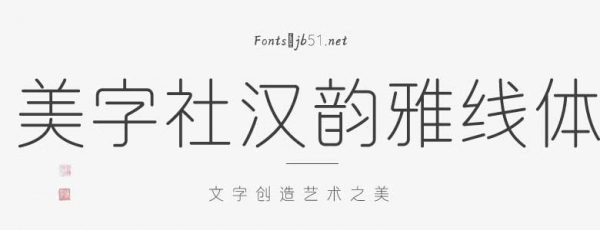
美字社汉韵雅线体晕染版
美字社汉韵雅线体晕染版以汉印和篆书结合,以极简设计手法创作的具有现代中国风的字体。字体融合了汉印的布局方正平直与篆刻的疏密轻重、方圆穿插;分为常规版和氤氲版,笔画转角柔和,结构透气合理;氤氲版在笔画交接处做了水墨晕染处理,版面观感舒适;中宫端正,字形优雅秀丽,在单线的笔画结构中保留圆润寻求变化的视觉效果。适用于文化、时尚、美妆行业的广告、海报、杂志等标题或正文用字。